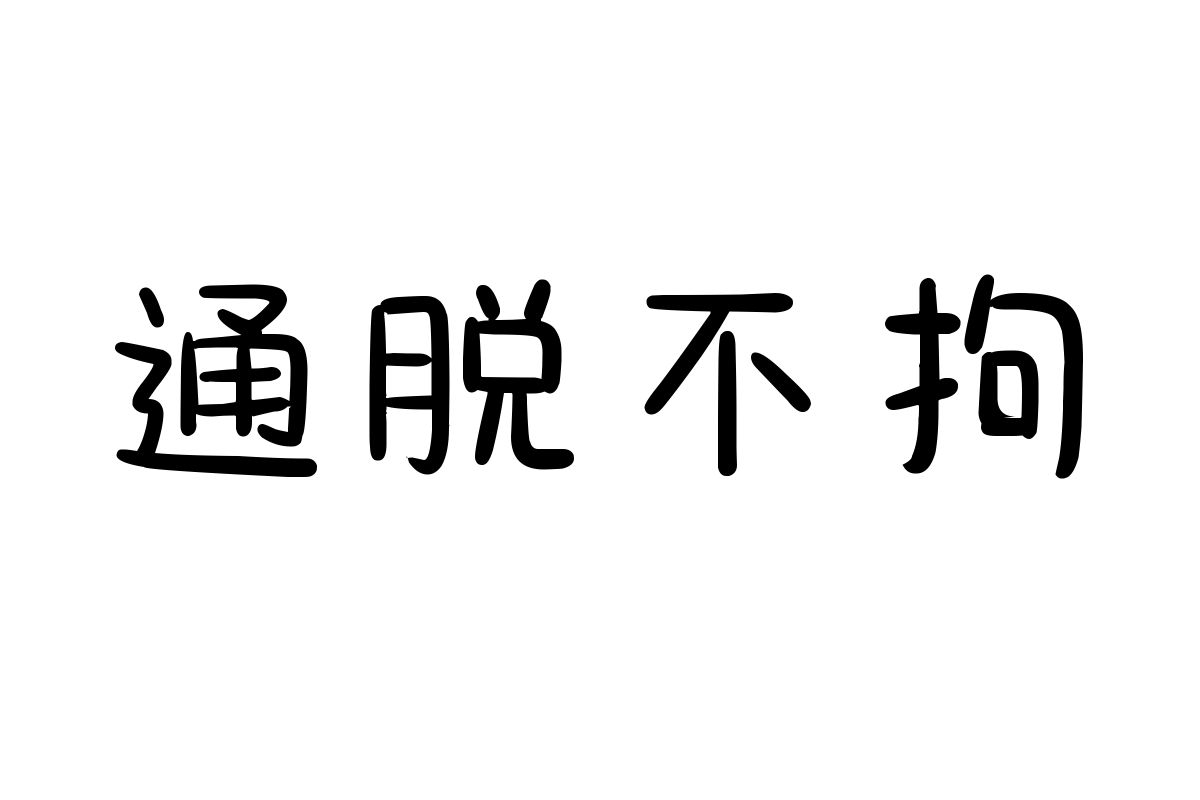
也字工厂啵啵体是一款现代感十足的中文字体,由北京也字工厂设计。这款字体具有独特的风格和特点,适合用于需要强调现代感和时尚感的场合。
该字体采用了简洁、流畅的线条,使得文字看起来更加清晰易读。它的笔画粗细适中,既能够展现出汉字的美感,又不会过于繁琐。同时,也字工厂啵啵体的字形结构紧凑,使得整体看起来更加协调。
此外,这款字体还具有一定的艺术感,能够给人一种轻松愉悦的感觉。无论是用于广告、设计还是其他需要突出个性和创意的场合,都是不错的选择。
总的来说,也字工厂啵啵体是一款独特而实用的中文字体,能够满足不同用户的需求。